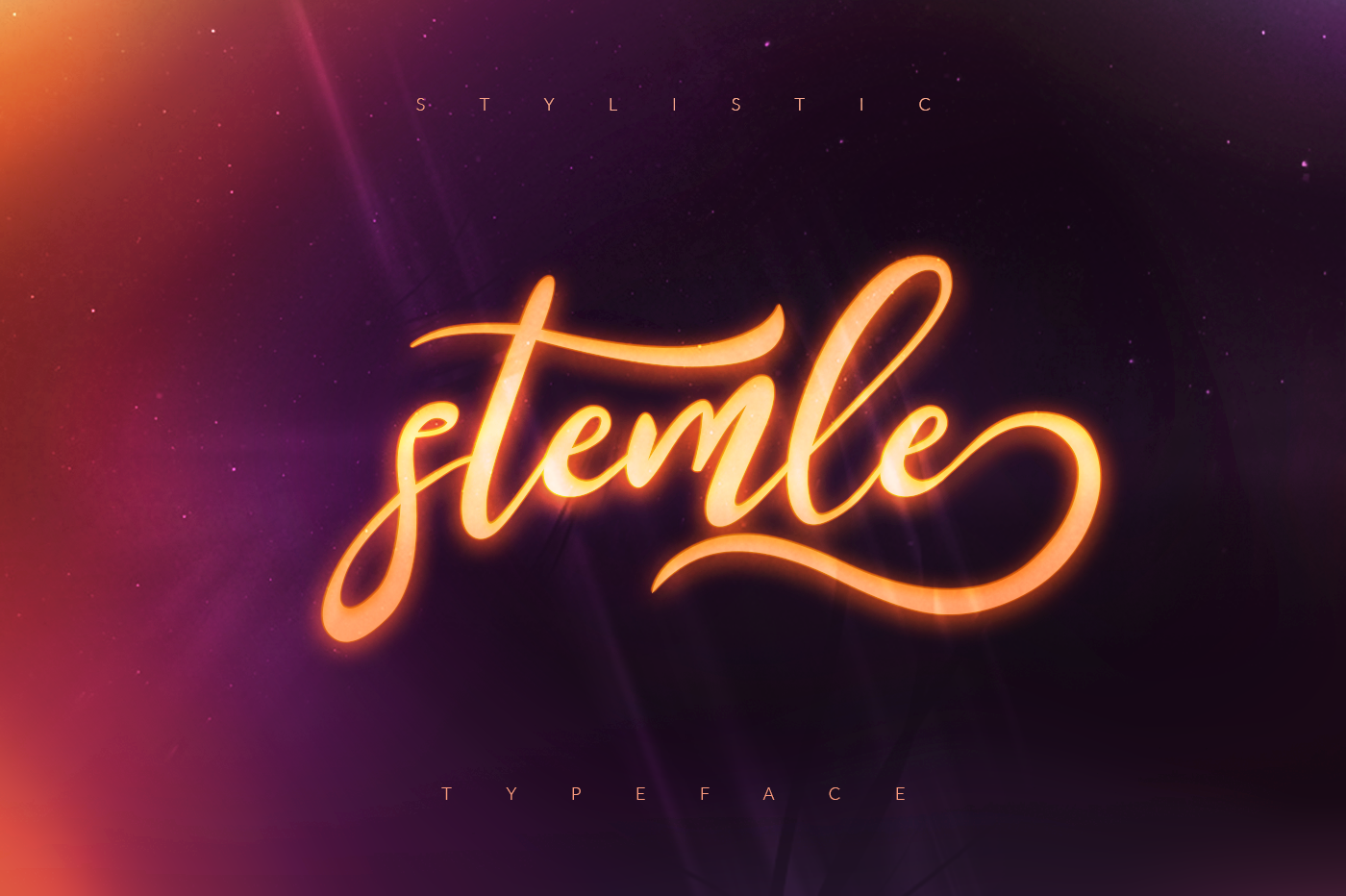
Stemle Stylistic Font – Download Grátis
Introduzimos a Stemle Stylistic Font! Desenvolvida por font art, esta fonte foi projetada pelo designer 178-MC e compartilhada com o mundo. O nome do projeto é STEMLE, mas preferimos chamá-la de Multi Purpose Font (Mpf), pois você pode usá-la em praticamente qualquer tipo de projeto. Isso acontece porque a Stemle Stylistic foi criada para ser versátil, e sua flexibilidade depende apenas da imaginação e criatividade do usuário. O Designer 178-MC nos ofereceu uma fonte original e única, com uma personalização stylizante que adiciona um toque diferenciado a qualquer texto. Essa característica de estilo é particularmente brilhante quando usada em projetos de design gráfico onde há um requisito para criar algo único e não padrão. Seja você designer web, ilustrador ou artista digital, certamente encontrará neste projeto uma fonte que pode ser usada no desenvolvimento de sites, criação de infográficos, produção de publicações digitais ou criação de vídeos. A Stemle Stylistic oferece mais do que apenas um efeito elegante e único – ela também é perfeita para quem busca diversidade em suas obras e deseja dar um toque especial a seus designs.